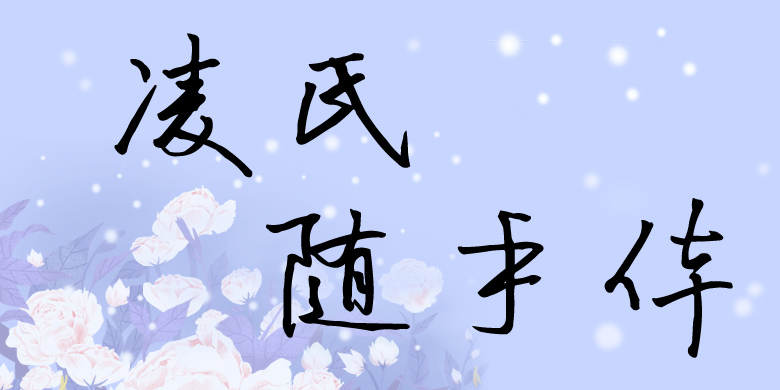
品牌:方正字迹设计师:刘殿儒发行时间:2016字库编码:大陆简体(GB2312-80)分类:常规书写·硬笔字体属性:精品字
这款字体笔画流畅飘逸,结体内紧外松,开合对比强烈,有比较强的视觉感染力。整套字气韵生动,行笔迅捷果断,具有浪漫洒脱的个性。适用于现代诗歌、短文的排版,以及文化、商业类品牌的广告语设计。